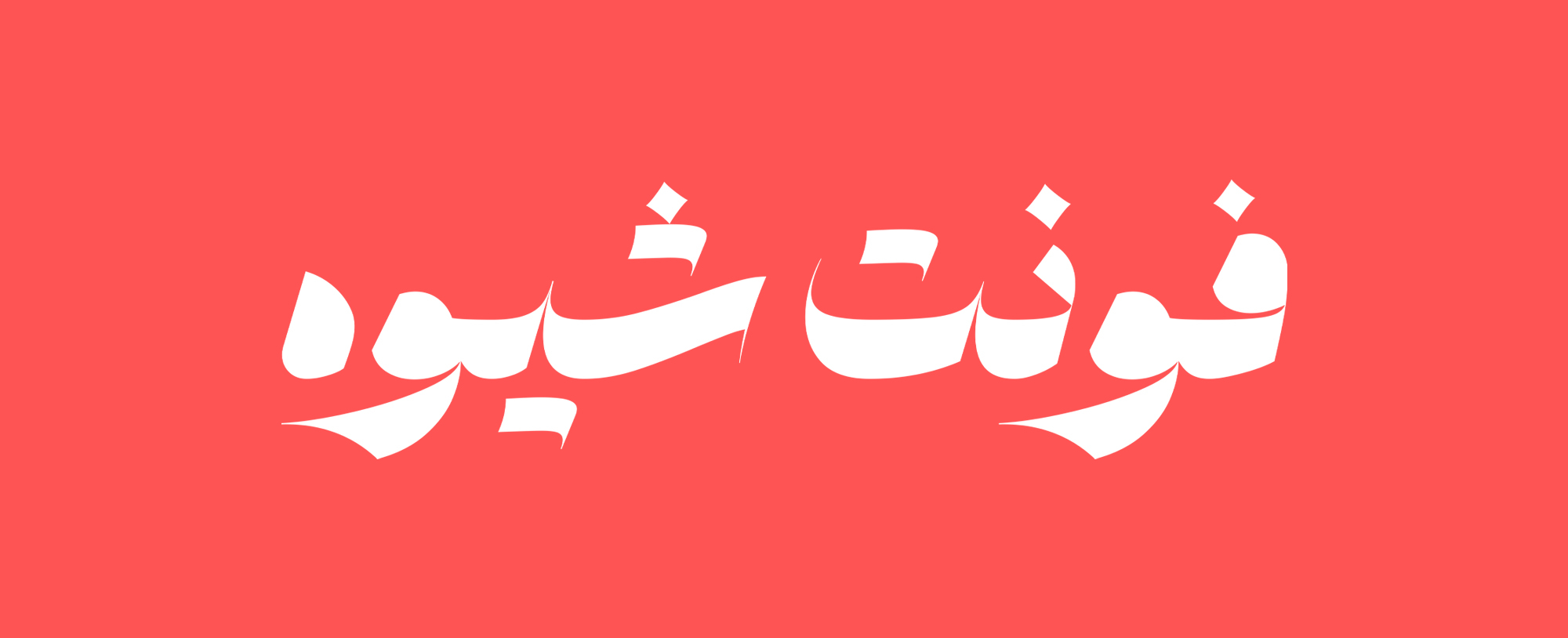
فونت شیوه
فونت شیوه یه فونت نمایشی سه‌حالته ‌ست. اگه دنبال یک تیتر متفاوت، شجاع و خاص می‌گردی، شیوه همون چیزیه که لازم داری. شیوه سه تا استایل داره:
• Sticky که فرم‌هاش نرم و کش‌دارن و یه حس عجیبی بین سنتی و دیجیتال داره.
• Sharp با لبه‌های تیز و محکم؛ جدی، عصبی و آماده‌ی درگیری.
•  Stencil  کاملاً هندسیه و طراحیش دقیق و ساختاریافته است. خطوط صاف و برش‌های مشخصی داره که خیلی جدی و محکم توی چشم می‌زنه.
شیوه اصلاً برای متن‌های بلند ساخته نشده. فونتیه که باید در چند کلمه بدرخشه، بزنه تو چشم و رد شه. اگه دنبال یه فونت تیتر برای پوستر، کاور، برند یا طراحی جسورانه‌ هستی، شیوه خودش یه استایله.
فونت شیوه، الهامش از فرم‌های نسخ سنتی بوده ولی اونقدر باهاش بازی شده که تبدیل به یه فونت خشن، خاص و گرافیکی شده. اینجا دیگه خبری از تعادل و خونسردی نیست. هر استایلش یه شخصیت جدا داره، ولی همشون یه چیز مشترک دارن: دیده شدن.